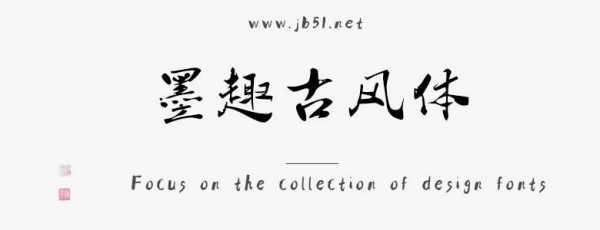
墨趣古風(fēng)體字體筆觸適中,字形端正,筆畫猶如行云流水,一氣呵成,每一筆都充滿了靈動性和連貫性,給人一種暢快淋漓的書寫美感,適合應(yīng)用于藝術(shù)設(shè)計(jì)、平面宣傳設(shè)計(jì)、網(wǎng)頁設(shè)計(jì),書法字帖等領(lǐng)域。有需要的朋友快來本站下載使用吧。
筆畫特點(diǎn) 線條流暢:字體的筆畫猶如行云流水,一氣呵成,每一筆都充滿了靈動性和連貫性,給人一種暢快淋漓的書寫美感,仿佛書法家在宣紙上肆意揮毫,盡顯筆墨韻味。
粗細(xì)變化豐富:筆畫粗細(xì)有明顯的對比,起筆和收筆處往往細(xì)膩精致,而在筆畫的轉(zhuǎn)折和關(guān)鍵部位則適當(dāng)加粗,使字體更具立體感和層次感,增強(qiáng)了視覺沖擊力,也體現(xiàn)了書法中輕重緩急的節(jié)奏變化。
富有韻律:筆畫的走勢遵循一定的韻律和節(jié)奏,或蜿蜒曲折,或剛勁挺拔,相互呼應(yīng),形成一種和諧的視覺韻律,如同優(yōu)美的樂章,讓人在欣賞字體的過程中感受到一種內(nèi)在的節(jié)奏感。
風(fēng)格特色 古風(fēng)韻味濃郁:整體風(fēng)格充滿了濃郁的古風(fēng)氣息,讓人一眼就能感受到傳統(tǒng)文化的深厚底蘊(yùn)。它汲取了古代書法藝術(shù)的精髓,融合了篆書、隸書、楷書、行書等多種傳統(tǒng)字體的特點(diǎn),將古典之美展現(xiàn)得淋漓盡致。
文化內(nèi)涵豐富:每一個字都仿佛在訴說著一個古老的故事,蘊(yùn)含著豐富的文化內(nèi)涵。從字體的形態(tài)和結(jié)構(gòu)中,可以看到古人的智慧和審美觀念,體現(xiàn)了中國傳統(tǒng)文化中對和諧、對稱、平衡等美學(xué)原則的追求。
藝術(shù)感強(qiáng):“墨趣古風(fēng)體” 不僅僅是一種文字表達(dá)工具,更是一件藝術(shù)品。它將書法藝術(shù)與現(xiàn)代設(shè)計(jì)理念相結(jié)合,既保留了傳統(tǒng)書法的韻味,又具有現(xiàn)代字體的規(guī)范性和實(shí)用性,適用于多種設(shè)計(jì)場景,能夠?yàn)樽髌吩鎏愍?dú)特的藝術(shù)氛圍。